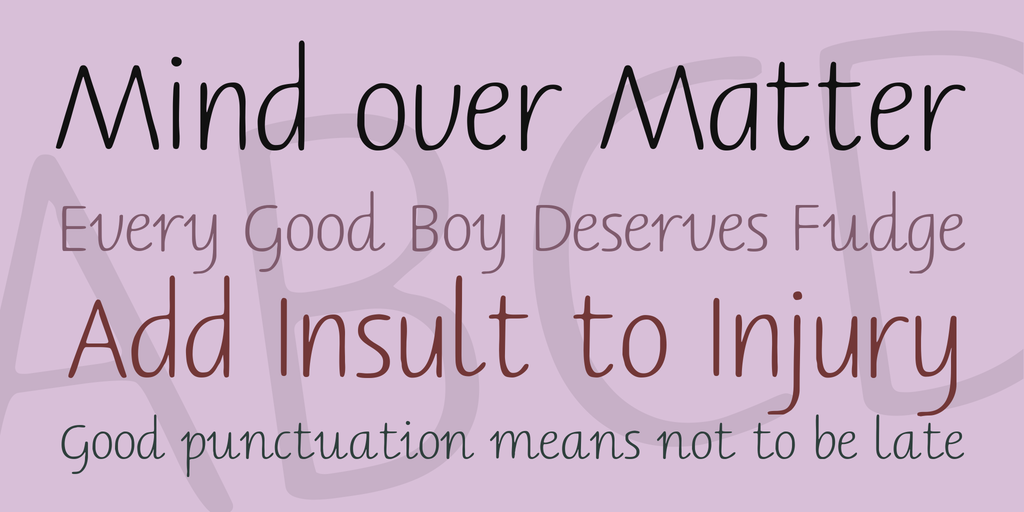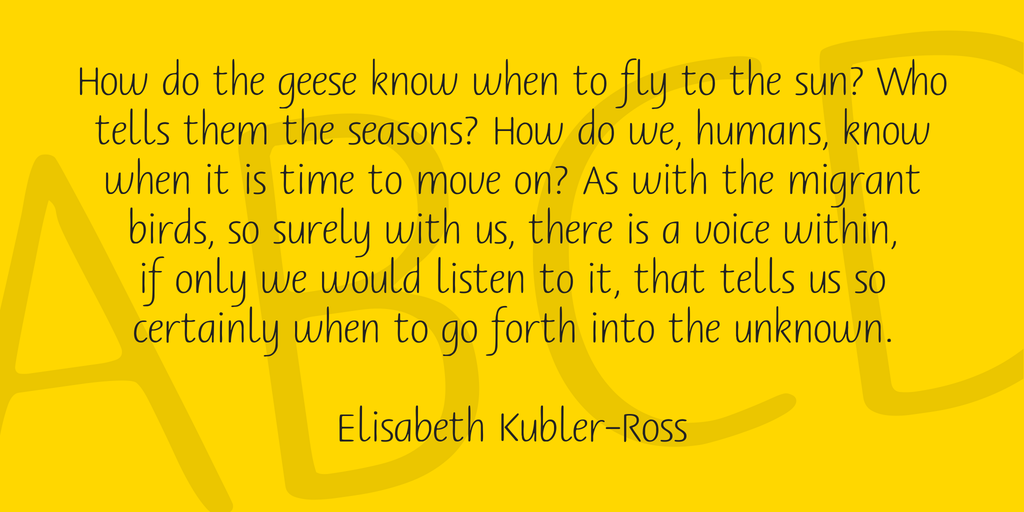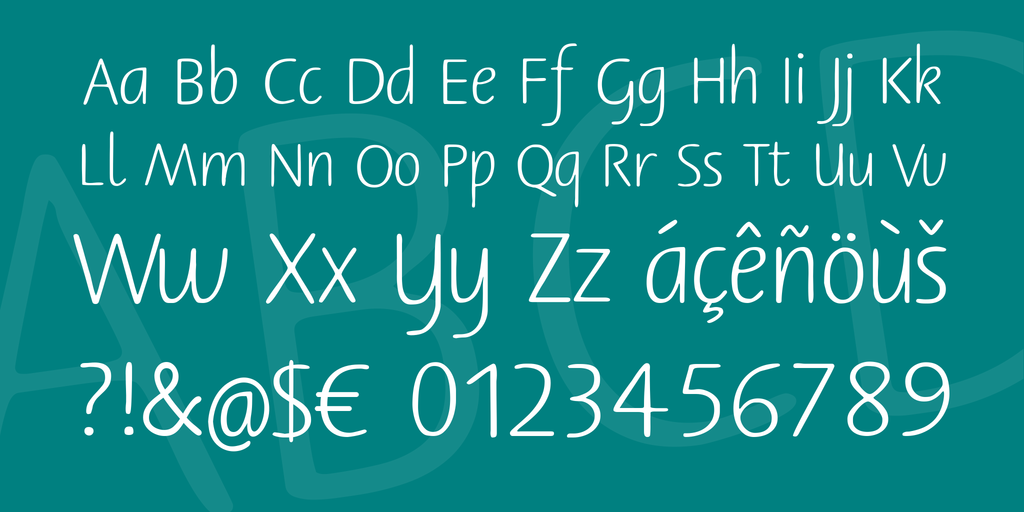
Berner Basisschrift FONT
diesem Ausspruch Heinrich von Sybels folgt das Konzept der Basis- bzw. Grundschrift. Es wird nicht mehr eine starre und komplett durchverbundene Schreibschrift gelehrt, welche für alle Schüler verbindlich ist, sondern man beginnt mit einer schon recht handschriftlich wirkenden einfachen Groteskschrift, welche nach und nach zu einer verbundenen Handschrift leitet. Aus welcher sich die Schüler hieraus selbst eine teilverbundene Schreibschrift entwickeln können. Dabei werden Verbindungen und dort geschrieben, wo sie sich aus den natürlichen Fluss der Handschrift entwickeln. Diese Schweizer Form geht hier allerdings ein wenig weiter. Beginnend mit der reinen Druckschrift Variante werden der Schrift in der zweiten Klasse einleitende und abschließende Bögen hinzugefügt, welche auf Verbindungen hin leiten.
Die Schrift der dritten Klasse, wie ich hier allerdings nicht anbiete, ist dann schon mit den entsprechenden leicht zu schreibenden Verbindungen ausgestattet, wobei die Schrift so konstruiert ist, dass sie sich gleichermaßen mit der rechten wie mit der linken Hand und ebenso gleichermaßen von Schülern die leichter mit oder gegen den Uhrzeigersinn kreisende Bewegungen ausführen können. Auch bei den Verbindungen werden dann Alternativen angeboten.
Wie ich schon sagte, biete ich hier nur die ersten beiden Schriftarten an, also die schlichte Grundform für die erste Klasse und die durch einleitende Anstriche und abschließende Grundbögen zur verbundenen Schrift hin leitenden Form. Ob ich auch die dann Teil verbundene Schrift Umsätze, die dann aber nicht für jede Software geeignet ist, da sie OpenType Funktionen enthalten muss, und ob ich diese dann hier auch anbieten werde, weiß ich bis jetzt noch nicht.